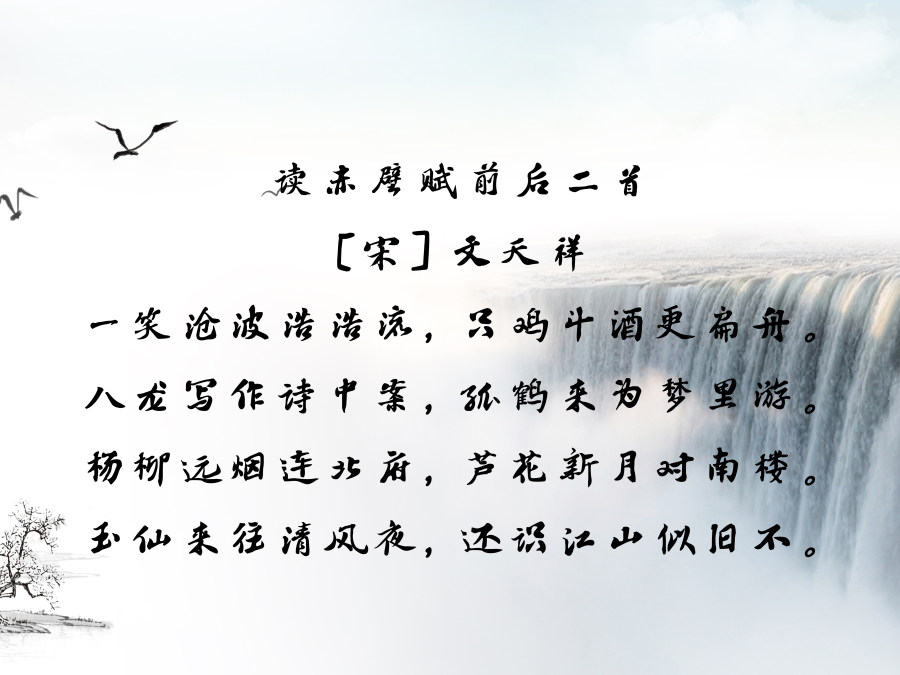
相信书法爱好者都知道李旭科书法,毕竟李旭科字体运用比较广,在书法爱好者当中是运用比较多的。因为李旭科字体具有艺术美感,有些设计运用比较多,那么在选择李旭科字体的时候应该选择哪个版本呢?可以从这几个方面考虑。
李旭科字体版本主要有两个,这是制作者李旭科自己说的,目前只推出了两款书法字体。一款是最早的李旭科毛笔行书字体,
另一个版本则是现在的李旭科书法体。李旭科字体结构泼洒奔放,入眼就会让人觉得很有书法韵味,所以不少书法爱好者非常喜欢这款字体。
李旭科字体非常的漂亮,虽然有两个版本,但每一个版本都让人觉得非常漂亮,很有书法韵味,所以运用的行业也比较多。像最早的李旭科毛笔行书字体就非常的适合想要学习艺术字体设计的爱好者,艺术美感非常的强烈,目前非常的受书法绘画者的喜欢,或者是艺术字体设计者的喜欢,在广告平面以及包装设计上运用的比较广。
李旭科字体有两个版本,书法爱好者在选择的时候可能会有一些苦恼,不知道是该选择最早的版本还是现在的版本,毕竟两个版本都非常漂亮,想要作出选择还真的非常困难。李旭科最早的那款版本是毛笔行书字体,这种字体可能会更适合于书法绘画,对于书法爱好者来说倒是一个不错的选择。书法爱好者在选择版本的时候,完全可以根据自己的喜好去做选择,没必要拘泥于哪一种版本,只要自己喜欢,适合自己风格的都可以选择。